回顧2025年,我們觀察到一個清晰的轉向:成功的品牌與產品,不再將字體視為單純的「美化工具」。面對跨文化誤解、資訊超載與AI同質化的挑戰,字體成為一項關鍵的「溝通工程」——旨在修復特定的體驗斷點,並構建無可替代的品牌護城河。
本文將帶您回顧蒙納在2025年的關鍵洞見、代表性案例,以及我們與各界攜手獲得的珍貴成果。
🎉 年度盛事:從在地對話到國際合作
2025年,蒙納透過一系列跨地域的活動與深度合作,持續強化與設計社群及產業生態的連結。除了於香港、台灣等東亞重要市場舉辦「Brand Talks」品牌對話系列,匯聚設計師、品牌策略師與行銷專家,共同探索字體在品牌演進中的核心價值與未來角色。
在跨界創新方面,我們與香港「設計營商周」(BODW)及台灣金點設計獎合作,共同促進設計思維與產業實踐的對話。我們更積極參與各地指標性盛會,將最新的字體知識與應用洞察帶給更廣泛的受眾。例如,我們在 Adobe Creator Link 中探討創意設計工作流程的未來;於 CYBERSEC 2025 臺灣資安大會 闡釋字體在資安與數位信任中的角色;在 DesignInspire 2025 展示視覺傳達的前沿趨勢;透過 Type Meet Hong Kong 與在地字體愛好者深度交流;並在 Hong Kong Design Summit 中與行業領袖共議設計的影響力。
蒙納的字體平台 Monotype Fonts 已匯聚超過 25 萬款字體,我們將 AI 技術深度融入平台,旨在幫助設計師跳過漫長的搜尋與試錯過程,將寶貴的時間與創造力,專注於更重要的策略思考與體驗設計本身。
同時,蒙納發布具有業界指標意義的《Type Trends Report》年度字體趨勢報告,今年更以全新策略框架,圍繞六大全球主題深度剖析,重新解讀字體在文化、科技與商業場景中所扮演的多元影響角色。
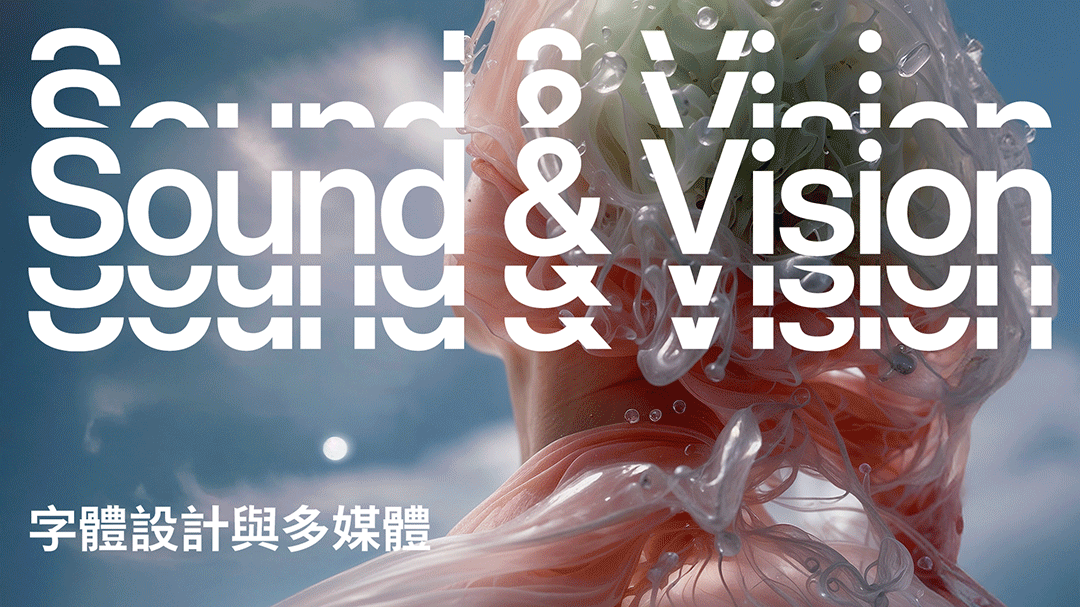
為進一步提升區域服務能量與技術支援體系,蒙納正式完成對韓國字體公司Design 210的收購,這項戰略布局將拓展我們在亞洲市場的設計服務範疇與本地化技術能力,為客戶提供更契合區域需求的解決方案。這些關鍵舉措,共同彰顯蒙納以持續創新、深度協作驅動設計未來的企業承諾。
1. 從「美感選擇」到「可讀性工程」—— 用字體為全球用戶構建無縫閱讀旅程
當你的用戶遍佈從中國到非洲,純粹的美觀字體便宣告失效。真正的挑戰在於:如何讓資訊在不同語言、不同裝置、不同閱讀習慣下,都保持清晰、高效與舒適。
實戰指南:挑對網頁字體,先懂這可讀性、兼容性、品牌感—— Top 10 最佳網頁字體
在數位體驗至上的時代,選擇網頁字體是一項關鍵的基礎工程。優秀的網頁字體必須在美學與功能性之間取得精密平衡:它需要足夠高的「x高度」以在小尺寸下保持清晰,擁有開放的字母造型和優化的字間距以減輕長時間閱讀的視覺疲勞,並能確保在不同螢幕分辨率下的渲染一致性。
案例分享:為非洲與新興市場「重新設計」閱讀體驗
我們與中國手機品牌傳音(Tecno)合作開發的 TransSans 字體,正是這一思維的典範。它並非另一個無襯線體的變體,而是針對非洲與亞洲多地區的螢幕特性、語言混合排版習慣(如阿拉伯文與拉丁文並存)及長時閱讀疲勞問題,進行的系統性工程設計。其目標直指一個可衡量的結果:消除多語言場景下的閱讀痛點,提升資訊獲取效率。
工具演進:Monotype Fonts 平台與 AI 如何成為設計師的「效能工程師」
Monotype Fonts 字體平台已有超過 25 萬款選擇。問題不再是「有沒有字體可用」,而是「怎麼快速找到最合適的那一款」。我們將 AI 深度融入平台,目的幫助設計師跳過漫長的搜尋與試錯過程,把時間和創意留給更重要的體驗設計。
2. 深入文化語境 —— 韓、日與東南亞語系的「字體推薦」
想要成功進軍新市場,關鍵第一步在於「像本地用戶一樣閱讀」——從語言的微妙差異、文化背景到閱讀習慣,都需深入理解。我們發現,蒙納的讀者對以下語言的字體設計特別感興趣:
韓文:〈18款精選韓文字體,詮釋現代設計語言〉
我們精選18款韓文字體,背後是觀察到其設計已超越K-Pop,融入全球UI/UX、產品設計與品牌塑造。它們成功將韓文特有的筆觸韻律,轉化為一種國際通用的現代感。
日文:〈贏得日本市場青睞的字體〉
進入日本市場,字體選擇是文化理解的試金石。我們解析哪些字體能脫穎而出,關鍵在於能否與那種極致追求「間」(空間)與「微調」的在地美學產生共鳴。
泰文:〈小米定製款很好用,這15款泰語字體也獨具美感〉
東南亞審美崛起:無論是與小米合作的泰文定製字體,還是我們展示的15款特色字庫,都證明該地區的設計正擺脫單純的「跟隨」,開始輸出獨特、自信的視覺語言。
3. 在AI生成時代,為品牌打造無法被複製的「視覺基因」
當AI能瞬間生成無數精美圖像與版式,品牌的視覺世界正面臨一場「平庸化危機」。在這樣一個充斥著相似審美、可預測風格的新環境中,如何確保品牌能被一眼認出、被深刻記住?答案在於構建無法被算法簡單複製的底層資產:一套深度植根於品牌DNA的字體系統。這已不再是奢侈品牌的專利,而是所有尋求長期差異化的企業的核心戰略投資。
案例分享:〈字體和奢侈品牌:時尚〉
頂級奢侈品牌早已明白,Logo的炫耀遠不及一套滲透於每個觸點(從官網、包裝到數字廣告)的品牌字體來得矜貴。它傳遞的是一種系統性的、無法被輕易模仿的品牌氛圍與節奏。
案例分享:〈Zettlab 的 AI NAS 不只拿下 2025 紅點設計獎〉
為何Zettlab的AI NAS能榮獲紅點獎?不僅是功能,其整體體驗的「完整度」至關重要。我們為其打造的專屬字體解決方案,確保了從硬體介面到行銷物料的視覺與交互高度統一,這份精緻的協調感,正是打動評委的關鍵細節。
趨勢驗證:為何全球品牌掀起「Logo簡化」浪潮?
從麥當勞到家樂氏,品牌簡化Logo並非放棄識別,而是將識別的重心從一個圖標,轉移到一套更靈活、更數位原生的視覺系統。在這套系統中,字體扮演了遠比過去更核心的角色,成為承載品牌價值的首要載體。
✨ 特別推薦:兩篇不容錯過的深度故事
除了趨勢洞察,那些蘊含歷史與文化厚度的字體故事,同樣引發讀者共鳴。
〈DIN:字體界的「德國製造」,如何紅遍全球?〉
這是一個關於「功能性如何昇華為文化符號」的傳奇。從德國道路標牌的工業標準,到成為全球信賴感與現代主義的代名詞,DIN的歷程揭示了經典設計的深層力量。
〈今年奧斯卡最佳影片,用到了這款字體!〉
字體是大銀幕的「幕後演員」。本文揭密奧斯卡獲獎影片背後的字體故事,看經典字型如何為電影海報定調,在方寸之間構建電影宇宙的第一重幻覺。
🌏 展望未來:持續融合美學、技術與在地需求
2025年,是蒙納與各界夥伴深化對話、紮實突破的一年。我們見證字體作為文化的載體、品牌的聲音與科技的介面,其戰略地位已無可動搖。